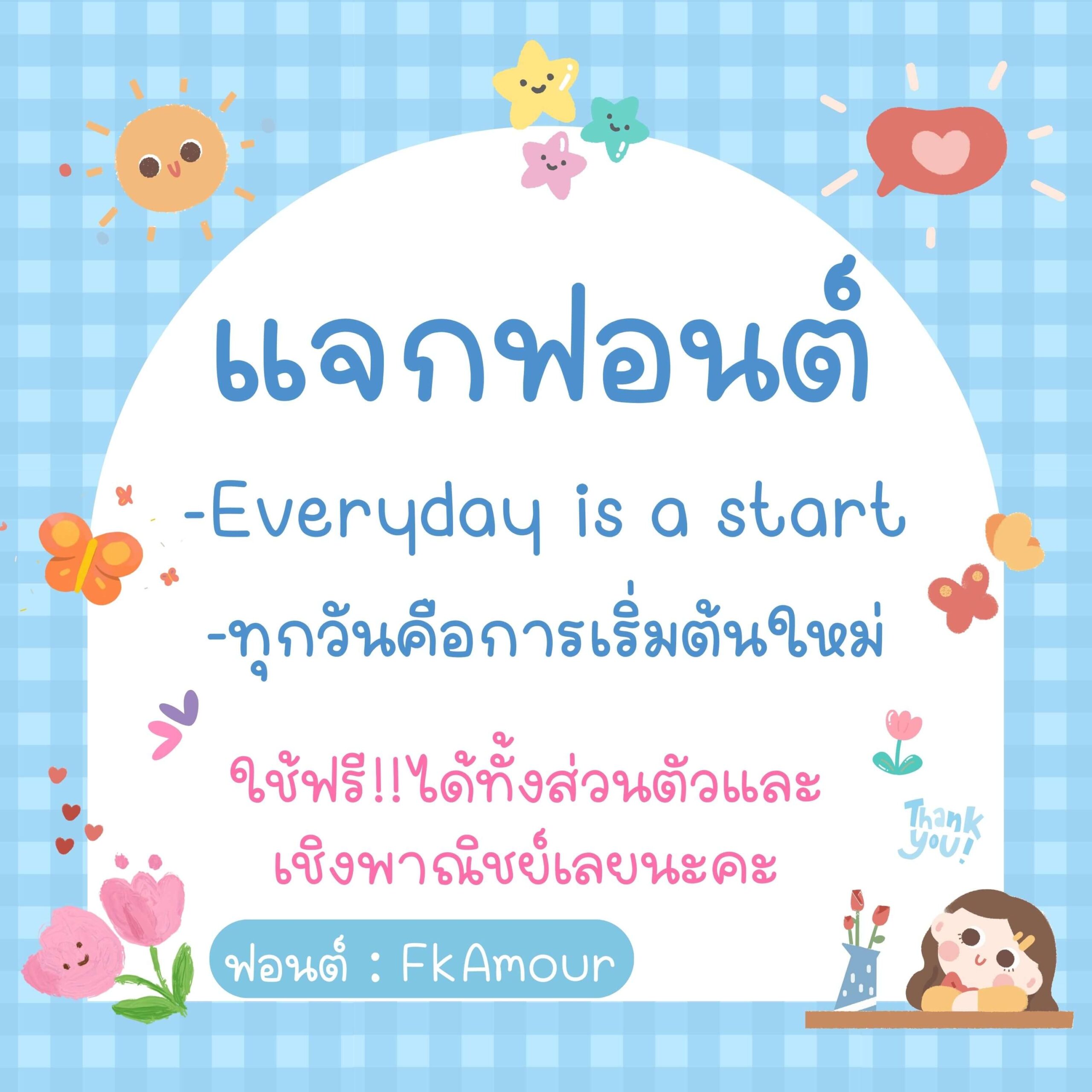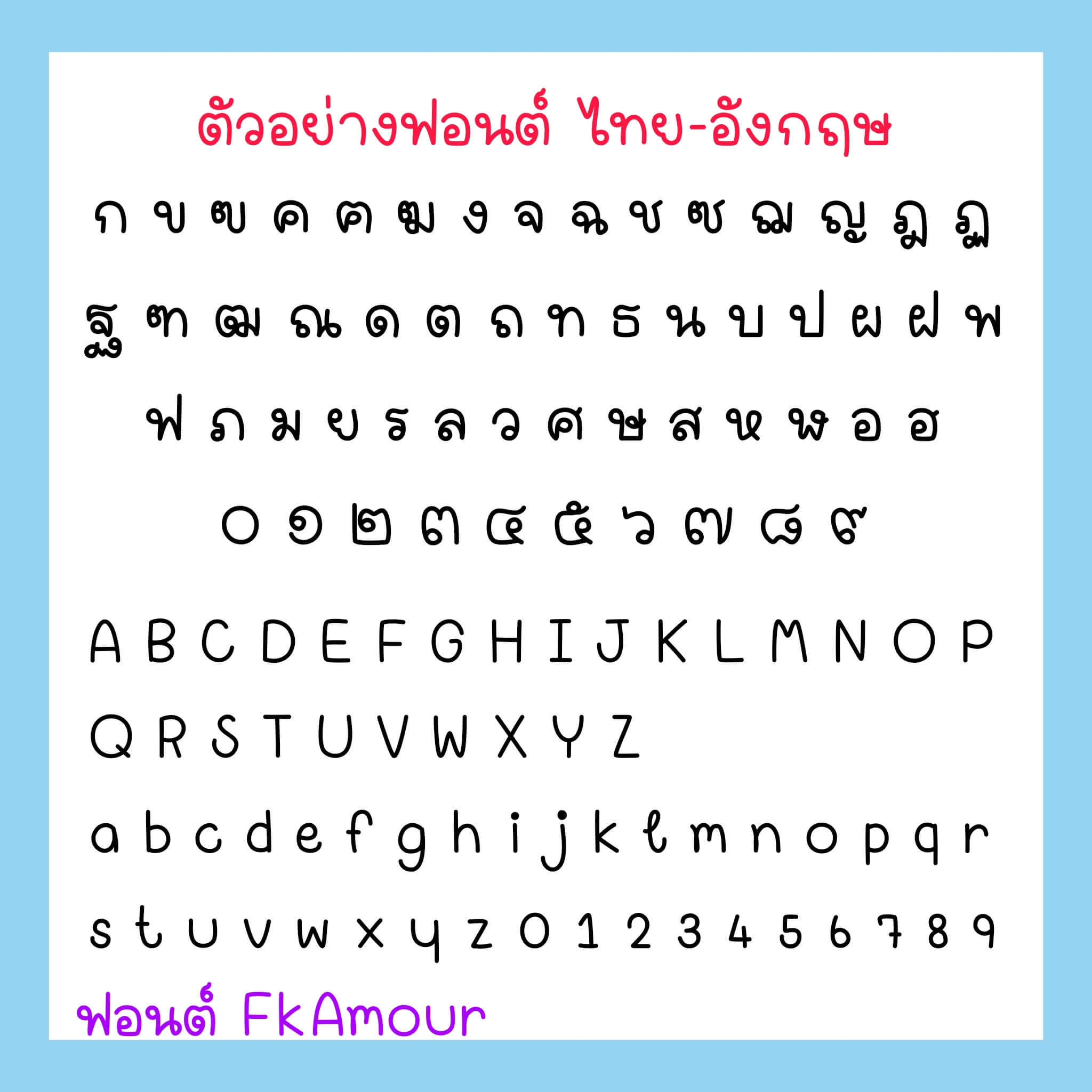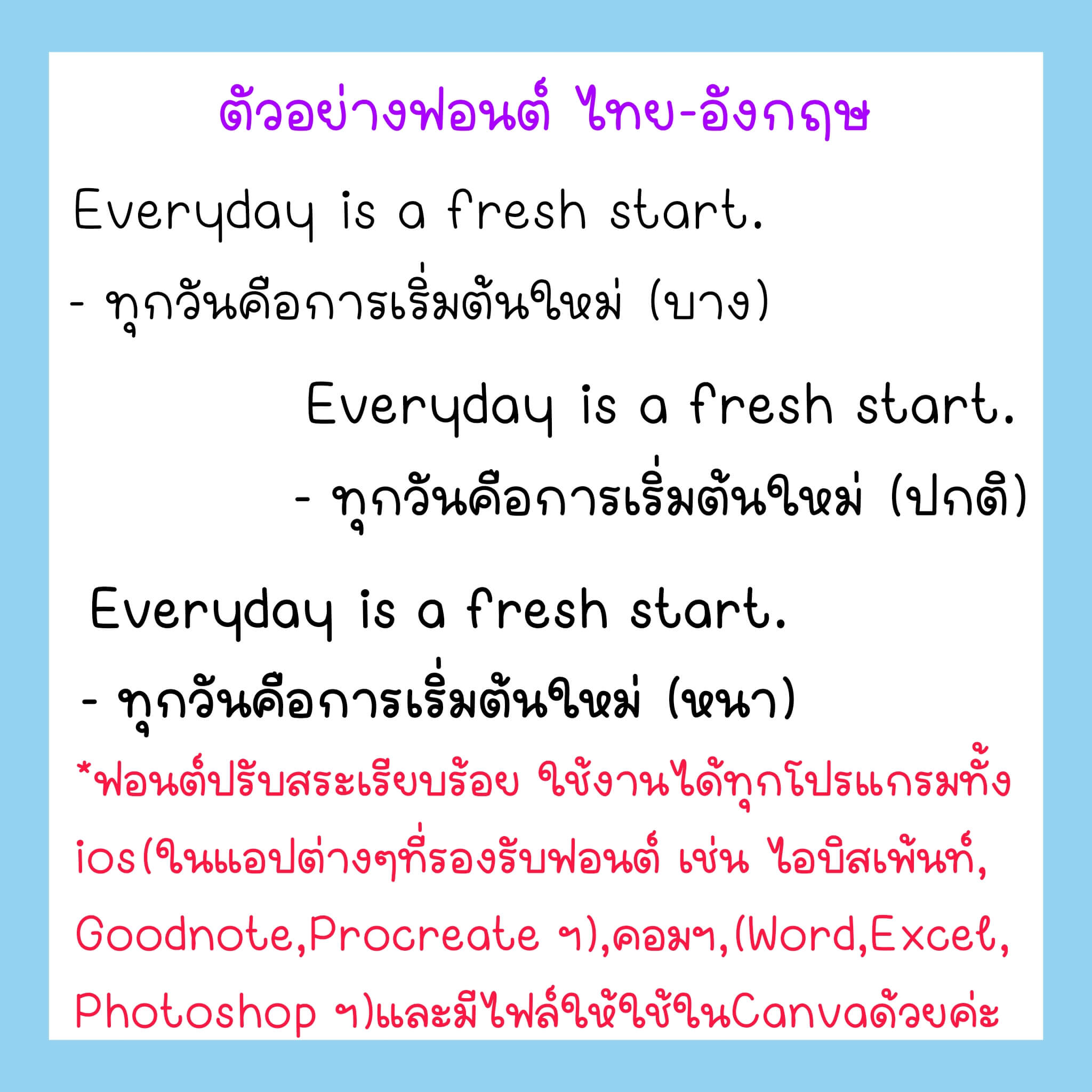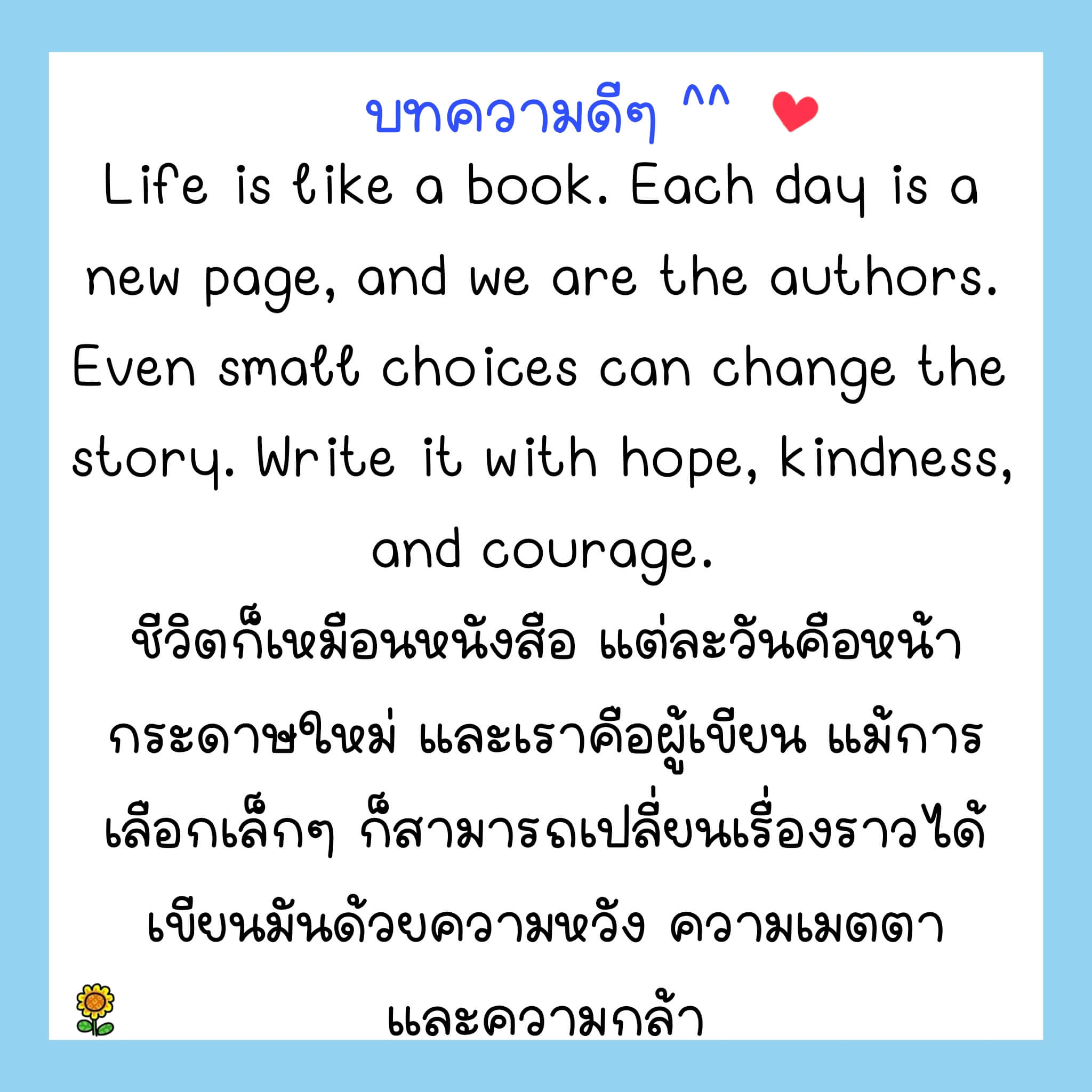
แจกฟอนต์จ้า ^^ ฟอนต์ FkAmour – ฟอนต์ลายมือแนวน่ารัก ตัวกลมๆอ่านง่ายสบายตาค่ะ ฟอนต์นี้สามารถนำไปใช้ได้ฟรี ใช้ได้ทั้งส่วนตัวและเชิงพาณิชย์ (ย้ำ!! ใช้ได้ฟรีทั้งส่วนตัวและเชิงพาณิชย์นะคะ)
FkAmour